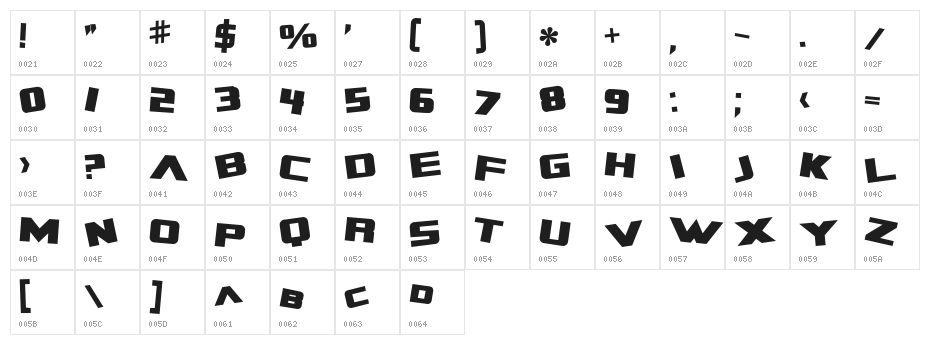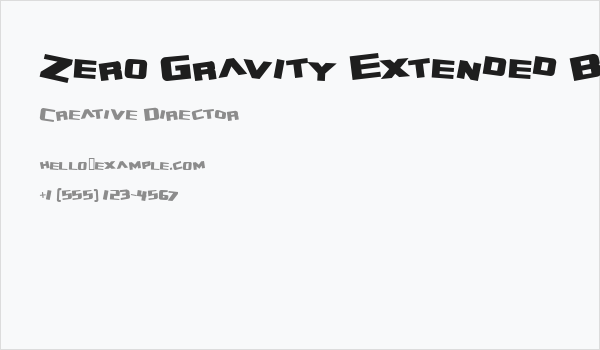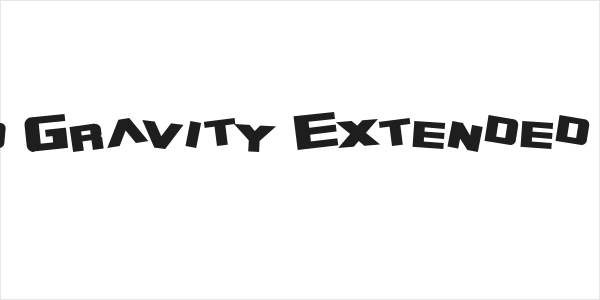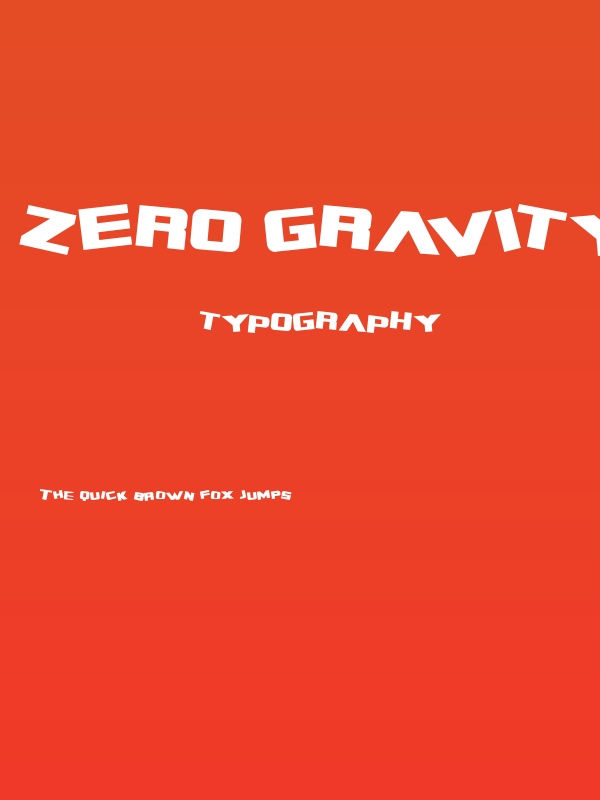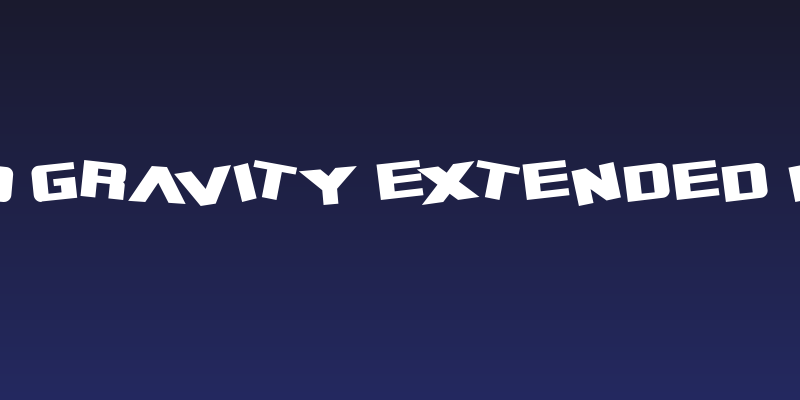
Zero Gravity Extended Bold Font
| Progetti proposti | Ideal for sci-fi themed posters, video game titles, futuristic branding, and dynamic advertising campaigns. |